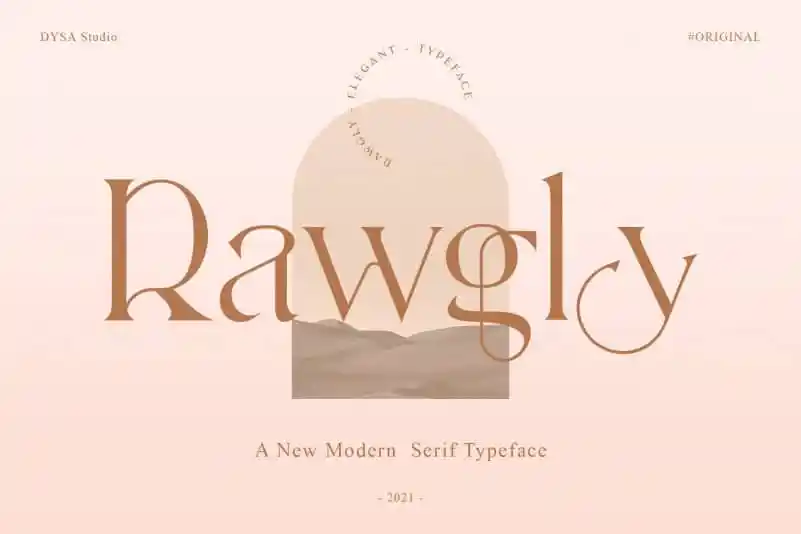
Rawgly Serif Font – Download Grátis
A Rawgly Serif Font é uma elegante tipografia serifada criada pelo designer dysastudio que se destaca por sua simplicidade moderna. Essa fonte perfeita para projetos de marca, logotipos, designs de casamentos, posts nas redes sociais, anúncios, embalagens de produtos, design de produtos, rótulos, fotografia, marcas d’água, convites e material de impressão. Suas linhas sólidas e harmoniosas aprimoram qualquer projeto visual, tornando-a uma escolha ótima para aqueles que buscam um equilíbrio entre sofisticação e simplicidade em sua identidade visual. A Rawgly Serif Font é um must-have para designers gráficos buscando uma fonte de qualidade com uma aparência moderna e elegante.